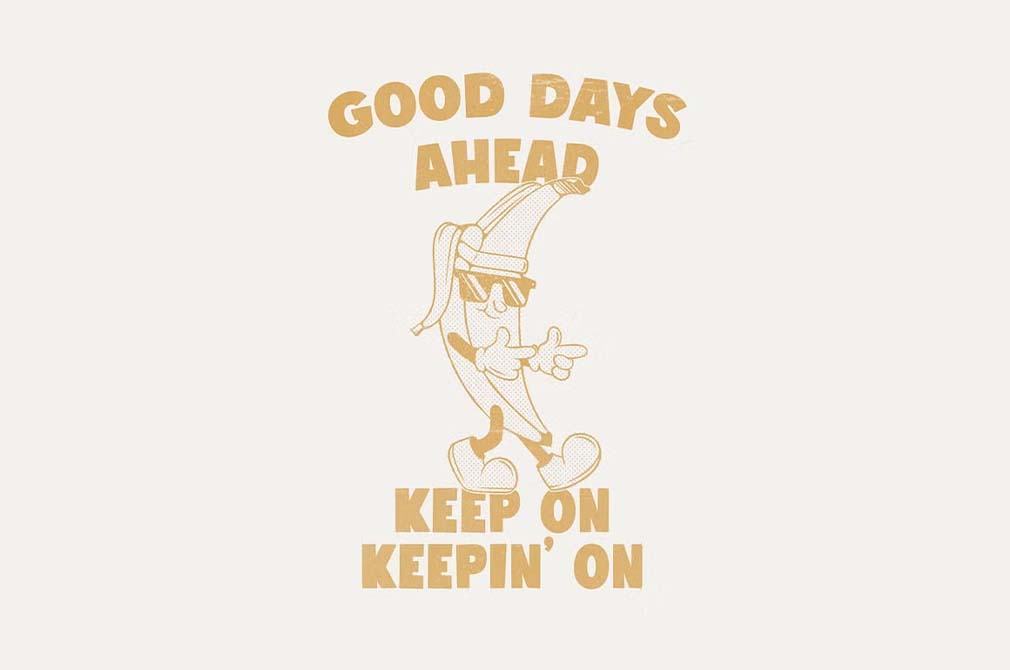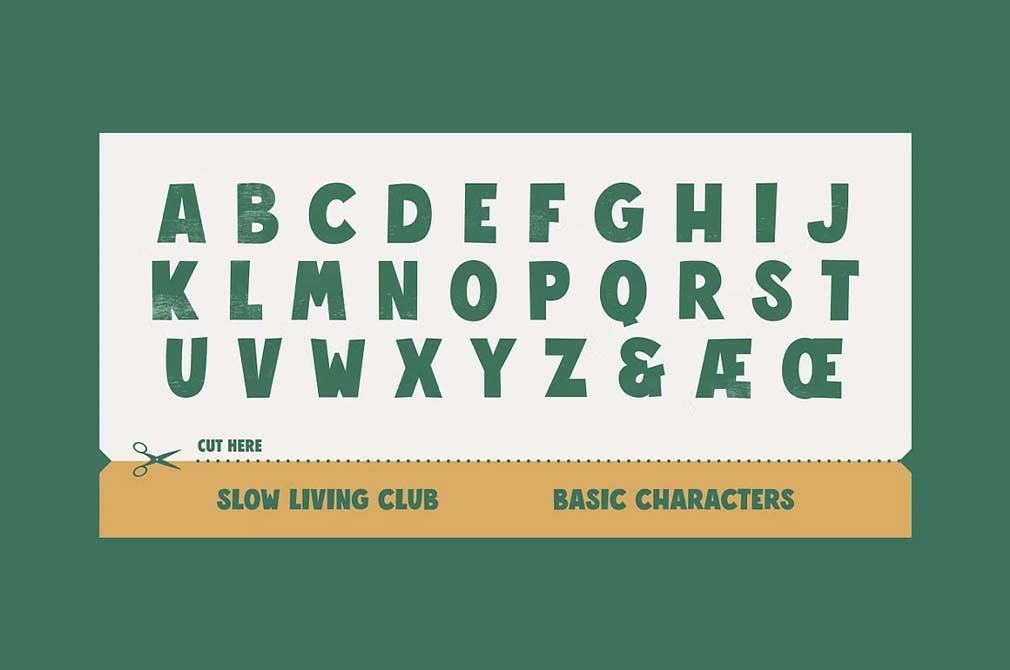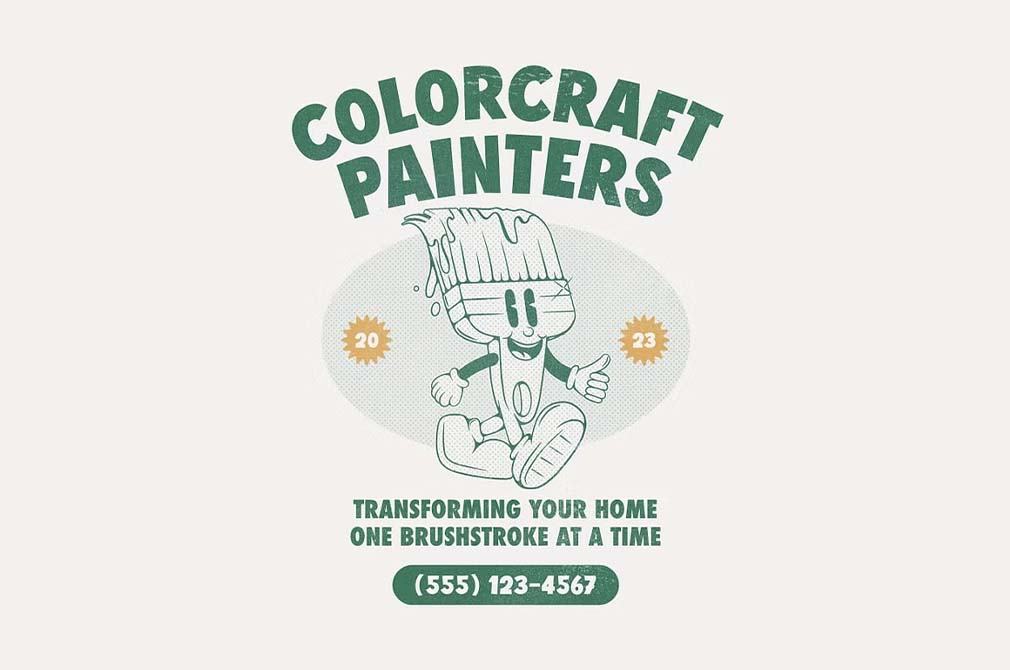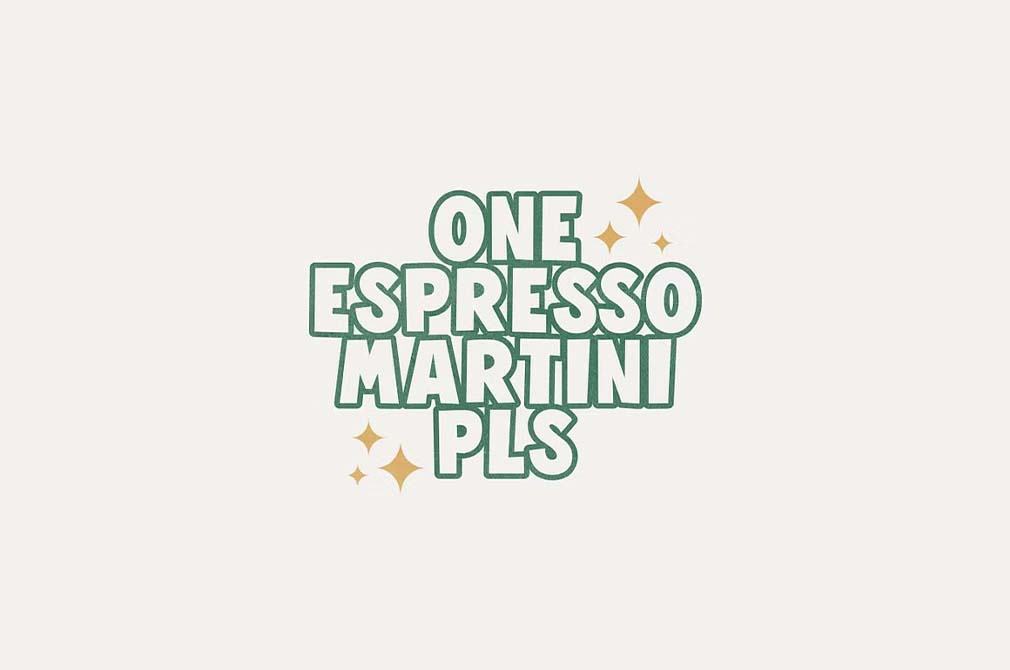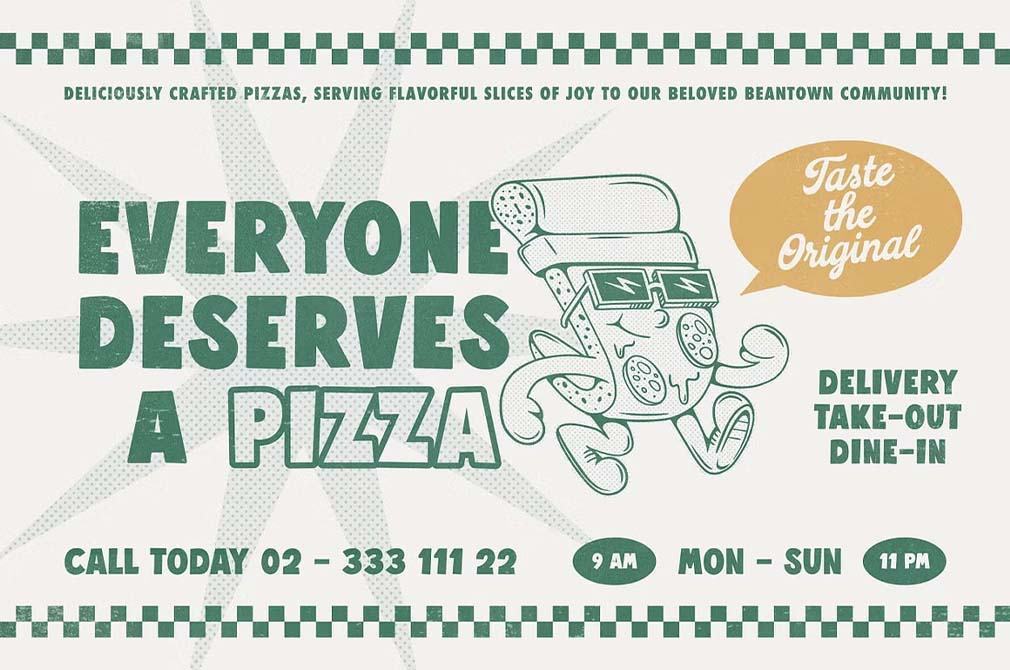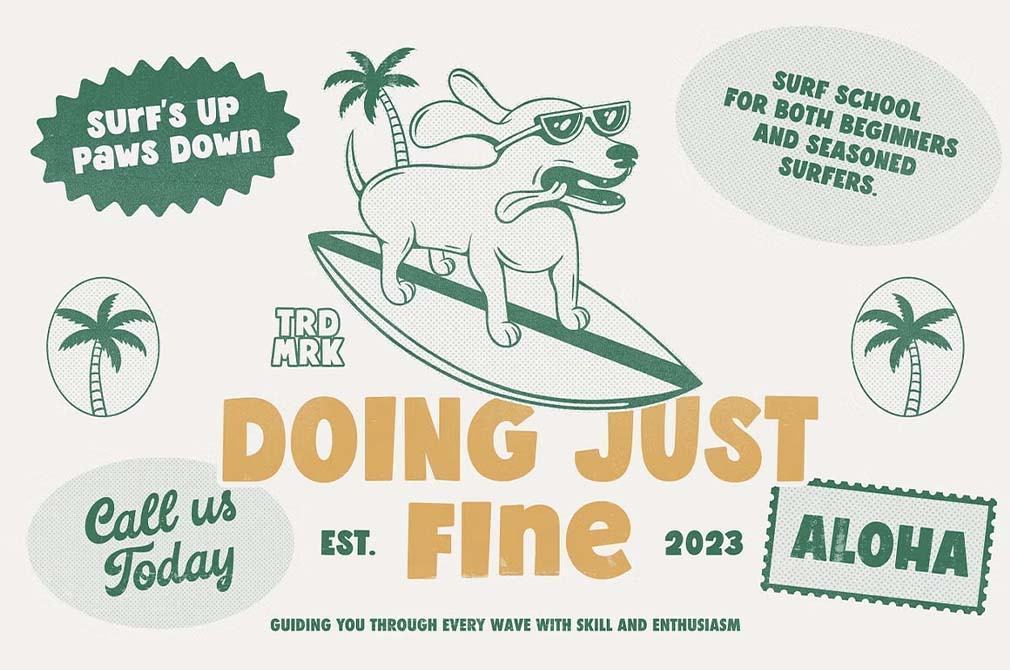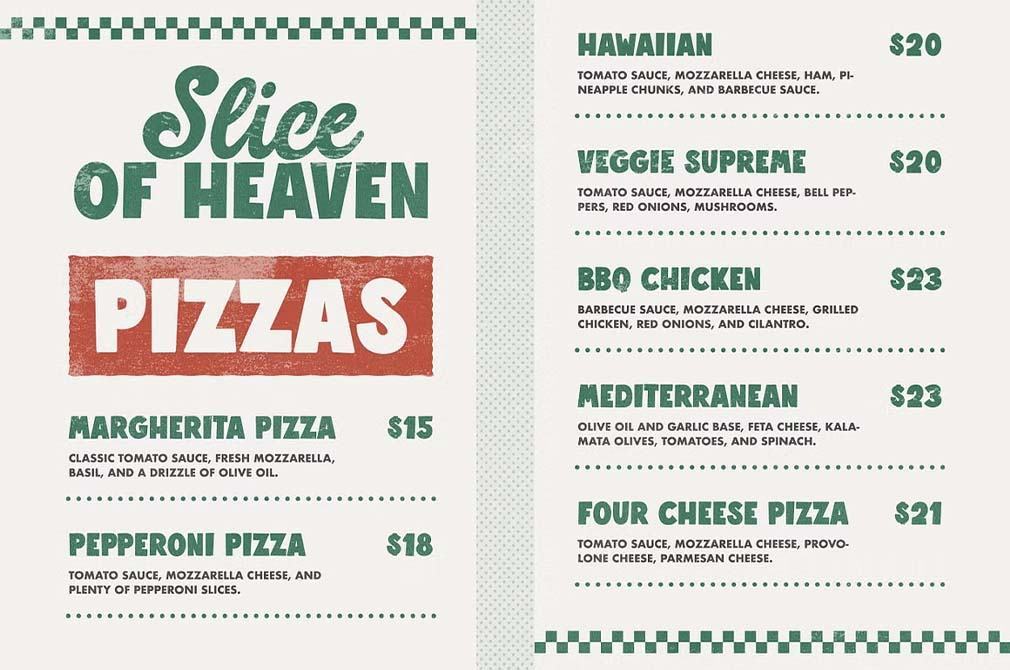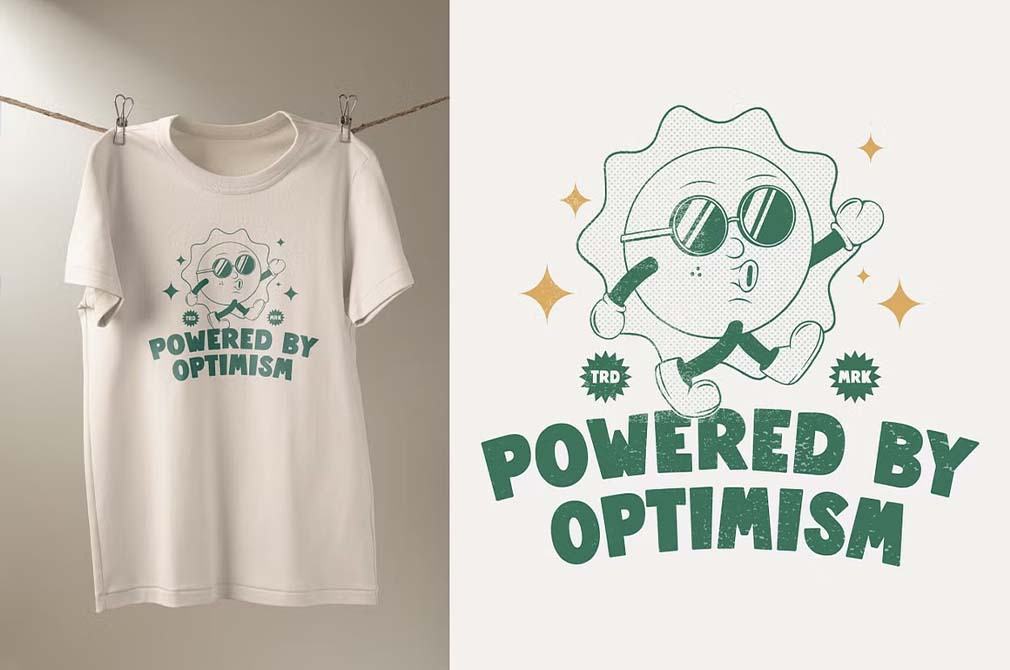
Phong cách “rubber hose” là một xu hướng đang được các họa sĩ minh họa ưa chuộng. Nhưng còn về font chữ thì sao? Ý tưởng tốt nhất là lấy cảm hứng từ phim hoạt hình những năm 1930 và các phiên bản hiện đại của chúng, như Cuphead hoặc Animaniacs.
Hãy làm quen với Slow Living Club, một font chữ sans serif mang đậm phong cách những năm 30. Font chữ này có 3 biến thể: clean, rounded và outlined, cho phép bạn phối hợp và kết hợp chúng. Slow Living Club sẽ là một bổ sung tuyệt vời cho các minh họa theo chủ đề, thương hiệu pizza, quán bar, tiệm xăm và DĨ NHIÊN là cả áo thun, đặc biệt là những chiếc áo có in hình các nhân vật hoạt hình retro. Slow Living Club có một bộ ký tự đầy đủ (bao gồm cả hỗ trợ đa ngôn ngữ) và 10 linh vật bonus ở định dạng PNG, AI và EPS.